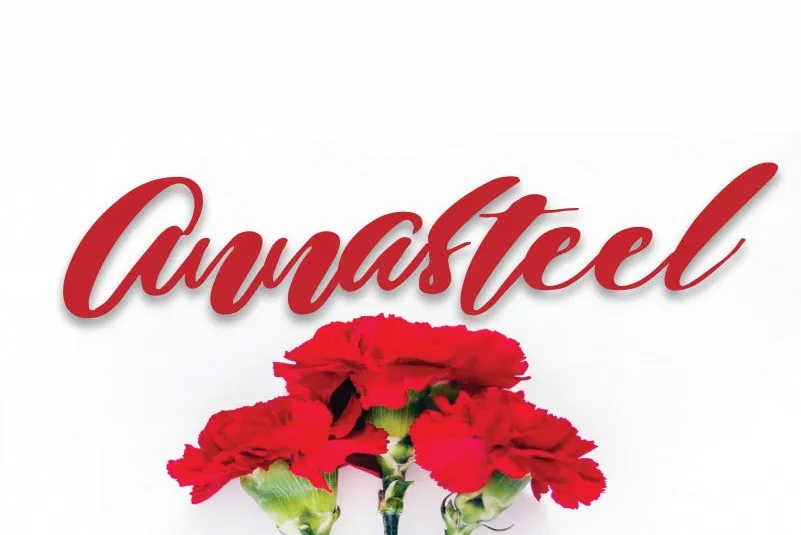
Annasteel – Bold Script Font – Download Grátis
A Annasteel – Bold Script Font é uma nova adição para aqueles que buscam uma fonte elegante e moderna no formato de script forte. Esta fonte é perfeitamente adequada para designers buscando um toque vintage sem perder o seu brilho contemporâneo. As suas linhas finas e detalhes sofisticados criam um aspecto encantador, ideal para uso em cartões de convite, cards de marca, peças de marketing, estilos de vida e até mesmo na criação de posters, tornando-a uma fonte indispensável no seu kit de ferramentas de design. Com ligaturas, alternativas estilizadas, conjuntos estilizados e acabamentos de swash, esta fonte não apenas enriquece a sua experiência visual, mas também eleva os seus trabalhos ao próximo nível. É um recurso gráfico indispensável para designers procurando por uma fonte versátil capaz de criar designs incrivelmente belos.